Tổng hợp font chữ Instagram tiếng Việt có dấu đăng story đẹp nhất
Những font chữ Instagram đẹp, độc lạ được chuyển đổi nhờ các web online sẽ giúp trang cá nhân của bạn sẽ nổi bật hơn. Hãy thử thay đổi font chữ trong phần tiểu sử hoặc nội dung khi đăng bằng những trang web sau đây. Chắc chắn tài khoản của bạn sẽ thu hút và nhận được nhiều lượt theo dõi hơn đó.
Có thể nói Instagram là một trong những mạng xã hội hot nhất hiện nay. Instagram có bộ font chữ riêng với tên gọi là Billapong. Tuy font chữ này đã rất đẹp so với các ứng dụng khác. Thế nhưng, toàn bộ người dùng đều sử dụng 1 font chữ thì trông chẳng có gì đặc biệt.
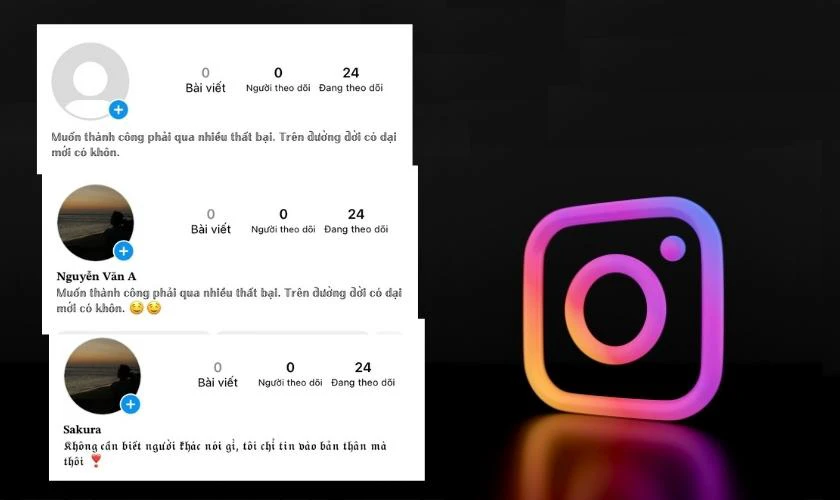
Vì vậy, hiện nay xuất hiện nhiều trang web hỗ trợ đổi font chữ Instagram. Điều này sẽ giúp trang cá nhân của bạn trông cuốn hút và bắt mắt. Bạn có thể được tăng thêm lượt thích và người theo dõi, dễ dàng xây dựng được thương hiệu cá nhân. Từ đó, công việc của bạn cũng sẽ thuận lợi hơn.
Muốn trang cá nhân, nội dung đăng tải trông lạ mắt, tăng nhiều lượt theo dõi. Bạn không thể bỏ qua những trang web đổi font chữ Instagram dưới đây.
Meta Tags sở hữu cả một kho tàng kiểu chữ vô cùng độc đáo để người dùng sử dụng trong Instagram. Với trang web này, bạn được quyền xem trước nội dung của bạn với kiểu chữ mà bạn đã chọn ngay trên giao diện của Instagram.
Bạn chỉ cần nhập nội dung vào mục EDIT TEXT ở phía trên cùng bên trái. Sau đó, màn hình sẽ xuất hiện các kiểu chữ mới. Hãy chọn font chữ mà bạn muốn rồi sao chép sang bài đăng Instagram.
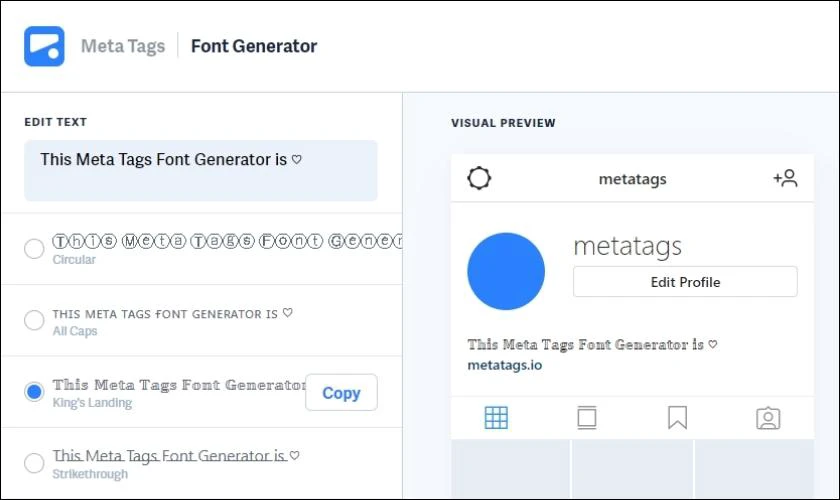
Với nội dung văn bản là tiếng Việt, nhiều kiểu chữ sẽ không hỗ trợ các từ có dấu. Do đó, nội dung hiển thị sẽ bị lỗi các chữ cái có dấu, trông nội dung thiếu chuyên nghiệp. Exotic Text chuyên cung cấp các font chữ tiếng Việt có dấu. Nhờ vậy, các chữ có dấu khi chuyển đổi sang font chữ khác không bị lỗi nữa.
Không chỉ thế, Exotic Text còn cung cấp cho người dùng ký tự đặc biệt trong font chữ và cả icon. Đoạn văn bản của bạn sẽ trông độc lạ, thu hút người đọc hơn nữa.
Hãy nhập nội dung bạn muốn vào ô trống trên cùng. Trang web sẽ tự động hiển thị các kiểu chữ với nội dung của bạn. Bạn chỉ cần lựa chọn font chữ mà mình yêu thích, rồi sao chép chúng dán vào Instagram.
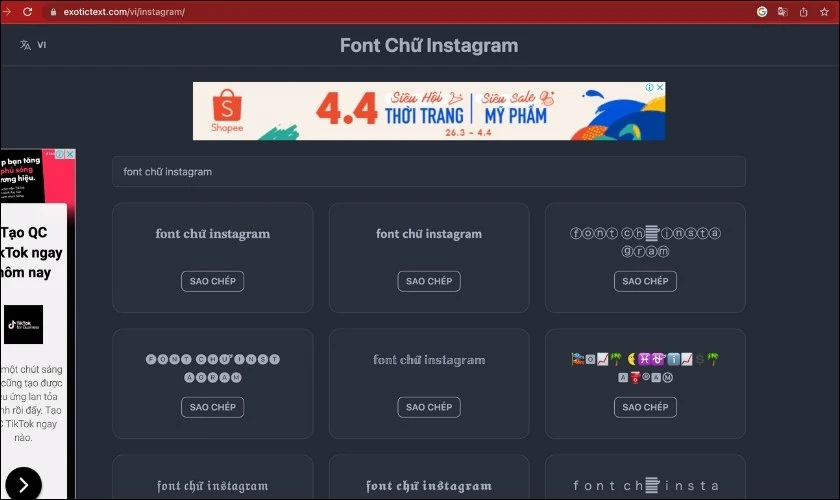
Tại trang web này cách đổi kiểu chữ sẽ đơn giản hơn. Bạn chỉ cần gõ nội dung vào thanh trên cùng. Instagram Fonts sẽ tự hiện ra nội dung của bạn đã được cập nhật các kiểu chữ. Bạn chỉ cần copy kiểu chữ bạn thấy thích.
Điểm thú vị của trang web này chính là nhiều font chữ Instagram được kèm theo các icon đáng yêu. Như vậy cũng sẽ giúp nội dung của bạn trông dễ thương và sinh động hơn.
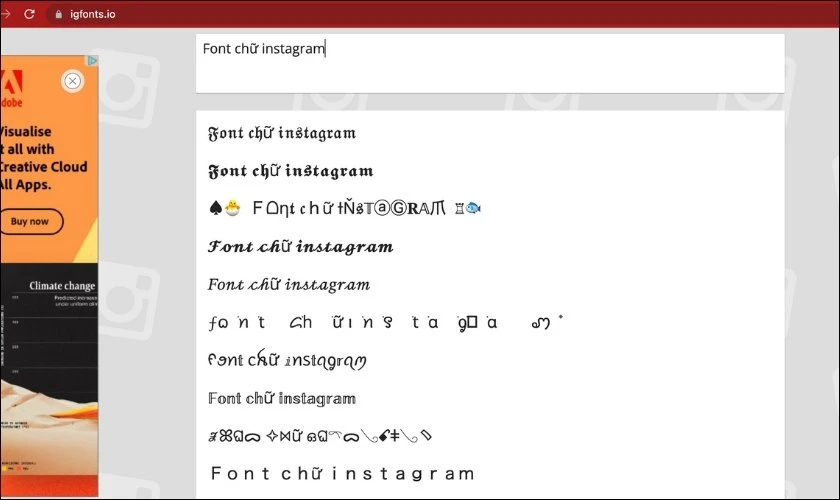
Instagram Fonts Generator có các kiểu chữ và icon đi kèm giống như Instagram Fonts. Cách sử dụng 2 trang web này cũng tương tự nhau. Điểm khác biệt duy nhất chính là, với Instagram Fonts Generator bạn sẽ không bị làm phiền bởi các quảng cáo hiển thị trong quá trình sử dụng.
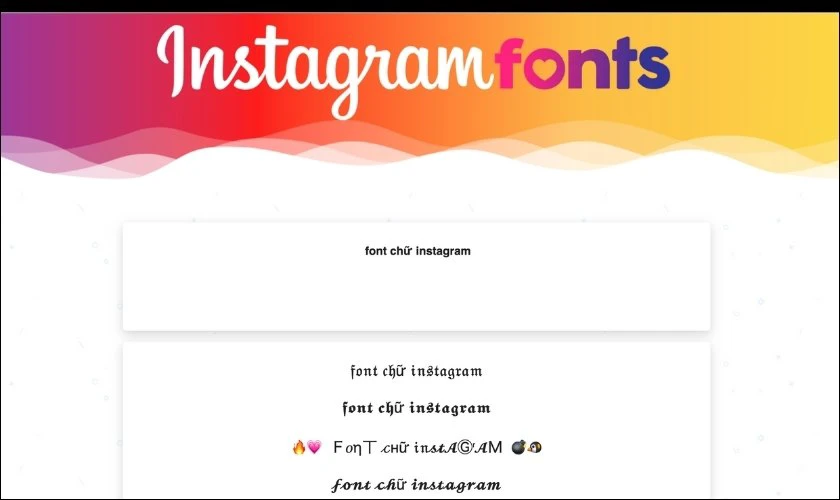
Trang web này sở hữu nhiều kiểu chữ nghệ thuật kết hợp với các biểu tượng cảm xúc. Đặc biệt hơn, Font for Instagram lại có giao diện hoàn toàn khác. Phần nhập nội dung sẽ nằm bên trái màn hình, bên phải sẽ hiển thị nội dung với nhiều font chữ Instagram khác nhau.
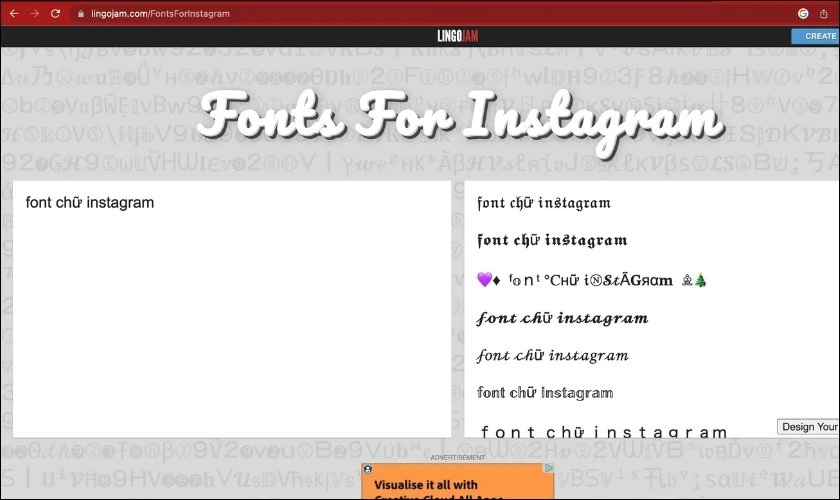
Nếu bạn đã quá chán với các font chữ Instagram đã có sẵn. Hãy thực hiện đổi sang các kiểu chữ khác để tạo ra dấu ấn của riêng bạn. Hai cách đổi kiểu chữ sau đây sẽ làm cho trang cá nhân, bài đăng của bạn trở nên khác biệt hẳn. Như vậy cũng dễ dàng gây ấn tượng với người khác.
Tiểu sử trên Instagram là nơi giúp bạn thể hiện được tính cách, cũng như giới thiệu về bản thân. Vì vậy, bạn nên thể hiện tiểu sử với font chữ mới phá cách bằng cách sau:
Bước 1: Trước tiên, bạn hãy truy cập vào các trang web chuyển đổi font chữ trên. Gõ đoạn văn bản rồi chọn cho mình một font chữ yêu thích. Sau đó, sao chép chúng.
Bước 2: Truy cập vào trang cá nhân trên Instagram. Sau đó, chọn vào Chỉnh sửa trang cá nhân.
Bước 3: Tại mục Tiểu sử, hãy dán nội dung bạn đã chọn font chữ qua các trang web trên. Cuối cùng, chọn dấu tích ở góc trên bên phải để xác nhận thao tác.
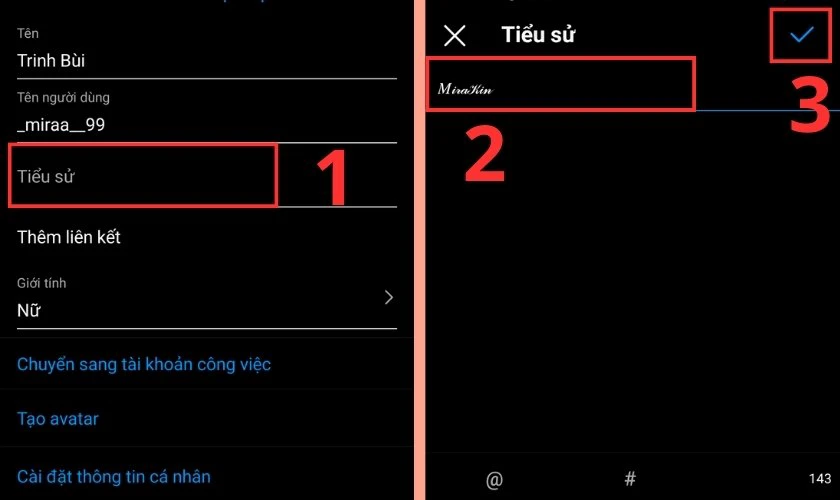
Việc lựa chọn font chữ như thế nào cũng giúp người khác thấy được một phần tính cách của bạn. Hãy sử dụng kiểu chữ mà bạn thấy yêu thích nhất nhé!